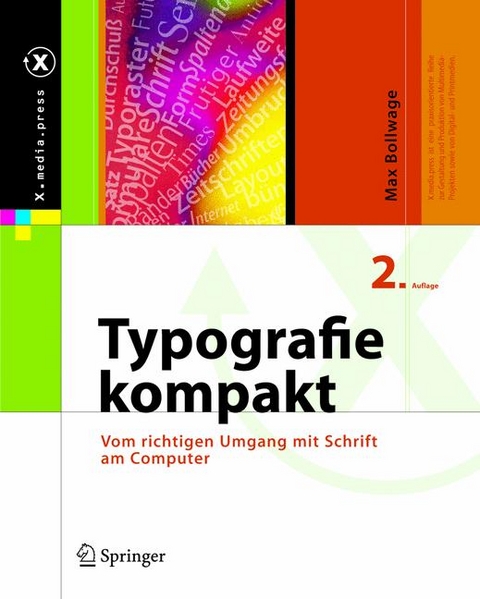
Typografie kompakt (eBook)
Vorwort: Die Regeln der Typografie gelten für Papier und Bildschirm 9
Das richtige Papierformat 10
Traditionelle Papierformate 11
DIN-Papierformate 12
Mehr Exemplare fürs gleiche Geld 13
Achtung Laufrichtung! 14
Zeitschriften- und Prospektformate 15
Zeitungsformate 16
Vom Bogen zur Rolle 17
Buchgrößen und ihre Verwendung 19
Bücher und ihre Proportionen 21
Plakatformate 23
Ränder und Satzspiegel 24
Der Computer fragt nach den Rändern und meint den Satzspiegel 25
Ein Vielzweck-Satzspiegel 26
Arbeiten mit dem Vielzweck-Satzspiegel 27
Ein Satzspiegel muss kein graues Viereck sein 28
Text-Bild-Kombinationen mit dem Vielzweck-Satzspiegel 29
Ein größerer Vielzweck-Satzspiegel 188 mm breit für DIN A4 31
Ränder und Satzspiegel im Buch 35
Gestaltungsraster für Schautafeln 41
Satzspiegel für einen Normbriefbogen 43
Satzformen und Abstände Typografie für den Bildschirm
Vom Leser und vom Lesen 45
Ausrichtung und Satzform 46
Satzformenübersicht 49
Spaltenabstand 50
Zeilenabstand 51
Wechselnde Zeilenabstände 54
Wortabstand und Schriftstil 55
Ändern der Wortabstände 56
Buchstabenabstand oder Laufweite 57
Laufweite und Schriftgröße 58
Ausgleichen kann der Computer nicht 59
Ligaturen und Unterschneidungen 61
Typografie für den Bildschirm 62
Die passende Schrift 64
Mit Bildern hat es angefangen 65
Sicher durch den Schriftendschungel 67
Die Ordnung der Druckschriften 70
Die Druckschriften im Überblick 71
Beschreibung der Gruppen 73
I. Antiquaschriften 73
II. Groteskschriften 77
III. Egyptienneschriften 79
IV. Auszeichnungsschriften 81
V.Geschriebene Schriften 83
Schrift kann mehr als Inhalte transportieren 85
Schriftstärke und Schriftbreite 87
Die Standard-Schriftformen und das Chaos der Bezeichnungen 88
Die richtige Schriftgröße 89
Buchstaben messen und beschreiben 91
Figuren einer Satzschrift - Minion von Adobe 92
Druckschriften richtig mischen 93
Buchstabenformen und Lesbarkeit 95
Typografie im Corporate Design 96
Corporate Identity und Corporate Design 97
Corporate Design und Typografie 98
Schritt für Schritt zum Corporate Design 101
Aufgaben der Typogra.e im CD 102
Das Firmenzeichen 103
Die Firmenschrift 104
Geschäftspapiere und Formulare 105
Externe Formulare 107
Bescheinigungen, Zeugnisse, Urkunden 109
Interne Formulare 110
Einheitliche Drucksachengestaltung 111
Personalanzeigen 113
Typogra.e für die Straße 115
Kleine Werbegeschenke 119
Tragetasche aus Papier 120
Bekannte Schriftzüge aus Satzschriften 121
Was Sie noch wissen sollten 122
Texte werden für Leser geschrieben – für die sollten sie auch gestaltet werden 123
Wie man Texte durch Absätze gliedern kann 124
Wie man Textstellen hervorhebt 125
Wie man Initialen einsetzt 126
Wie man Tabellen setzt 127
Auch das Nichts hat seine Regeln 129
Hässlichkeit verkauft sich schlecht 130
Checkliste für die Drucksachengestaltung 131
Manuskriptberechnung 132
Wurde nichts übersehen? Abschluss-Check nach Indra Kupferschmid 133
Die versteckten Tastenbelegungen 134
Die Tastenbelegungen für Zapf Dingbats 135
Der Computer fragt nach den Rändern und meint den Satzspiegel (S. 24)
Der bedruckte Teil einer Seite ist der Satzspiegel. Er kann aus Text, aus Bildern oder beidem bestehen. Seine Proportionen sollten in Büchern denen des Formats angeglichen sein. Die Ränder sind der unbedruckte Teil. Sie umgeben den Satzspiegel oben, unten, innen und außen. Im Buch sollte ihr Verhältnis gut abgestimmt sein. Nicht immer funktioniert das übliche Schema: innen 2, oben 3, außen 4 und unten 5 Einheiten. Häu.g sind die innenliegenden Seiten eines Buches sehr stark gewölbt, so dass ein zu klein gewählter Rand innen das Lesen erschweren kann. Bei Werbedrucksachen kommt es nicht selten vor, dass ein Heftrand verlangt wird, und der sollte nicht unter 18 mm breit sein.
Am Computer wird der Satzspiegel vor dem Öffnen eines neuen Dokuments durch Bestimmung der Ränder festgelegt. Das bedeutet, dass man sich vorher überlegen muss, wie groß der Satzspiegel sein soll und wo er auf der Seite stehen soll. Eine Skizze dazu ist immer nützlich.
Ein Satzspiegel für alle Zwecke
Ich habe, aufgrund meiner langjährigen Erfahrung mit immer wiederkehrenden ähnlichen Aufgaben, einen universellen Satzspiegel entwickelt, wie er auf der gegenüberliegenden Seite dargestellt ist. Mit dem kann ich alle alltäglichen Aufträge im Format DIN A4 und kleiner lösen. Entsprechend der jeweiligen Aufgabe lege ich den breiteren Rand nach innen oder nach außen.
Wichtig ist die Vielseitigkeit der Spalteneinteilung, um Abwechslung ins Layout bringen zu können, ohne den Satzspiegel zu sprengen – was aber nicht verboten ist. Der immer gleiche 4 mm große Spaltenzwischenraum ermöglicht es, verschieden breite Spalten zu kombinieren, was für die Verteilung verschieden großer Bilder von Vorteil ist. Der Spaltenzwischenraum passt zu allen Schriftgrößen für den normalen Leseabstand. Im Allgemeinen reichen sie von 8 bis 12 pt; in der täglichen Praxis sind es gewöhnlich 9 bis 10 pt. Der Spaltenabstand ist in jedem Fall immer größer als die Wortabstände, sodass die Gefahr des Überlesens von einer Spalte in die andere nicht gegeben ist.